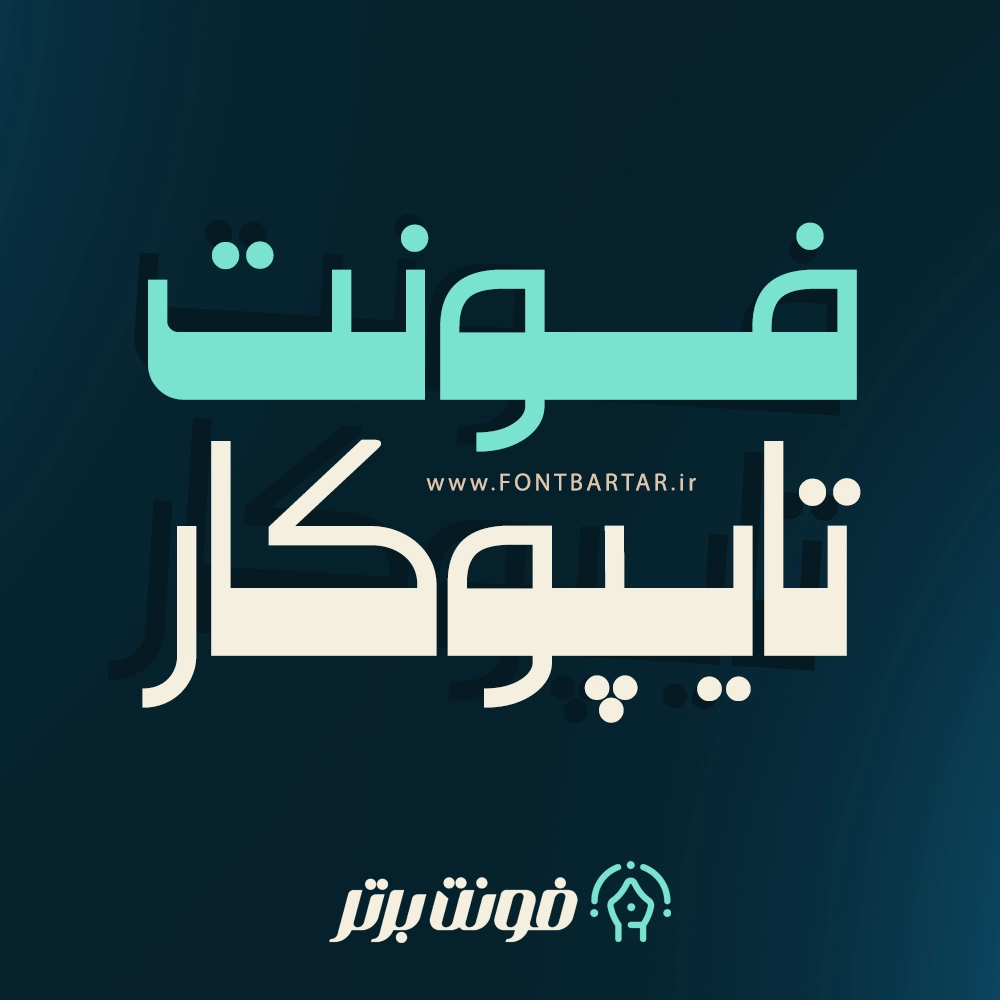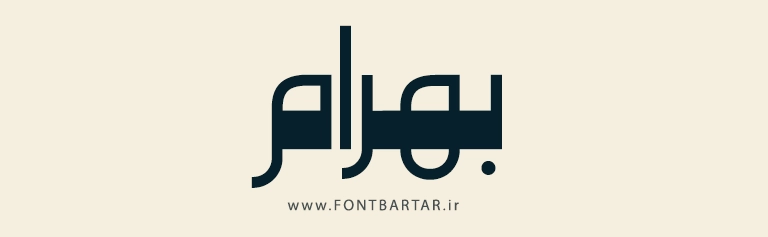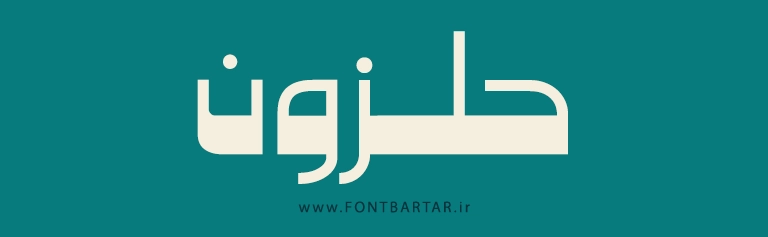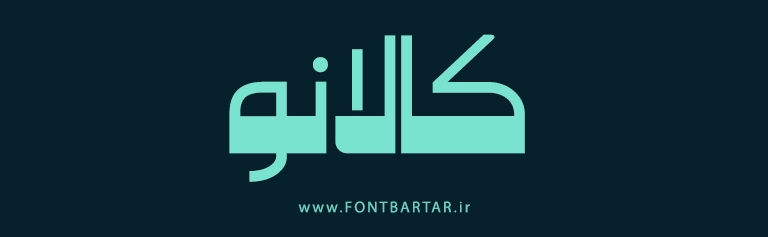
فونت زیبا و جدید تایپوکار
فونت خاص تایپوکار یک فونت منحصر به فرد و خلاقانه است که به دلیل طراحی خاص و جذاب خود، به عنوان یکی از بهترین انتخابها برای پروژههای تایپوگرافی فارسی شناخته میشود. این فونت برای طراحان گرافیک، وبسایتها و چاپگرها یک گزینه عالی محسوب میشود. در این مقاله، نحوه دانلود و استفاده از فونت خاص فارسی و کاربردهای آن را بررسی خواهیم کرد.
دانلود فونت خاص تایپوکار برای طراحی گرافیکی و تایپوگرافی فارسی
فونت تایپوکار به طور خاص برای ایجاد تایپوگرافیهای زیبا و چشمنواز طراحی شده است. این فونت ترکیبی از خطوط منحنی و زاویههای دقیق است که به متنی که در آن استفاده میشود، جذابیت و شخصیت خاصی میدهد. از این خرید فونت خاص میتوان در طراحی لوگو، بنرهای تبلیغاتی، و محتوای وبسایت استفاده کرد. طراحی آن به گونهای است که هم در اندازههای بزرگ و هم کوچک به وضوح قابل خواندن است.
مزایای طراحی با فونت خاص از فونت تایپوکار در طراحیهای گرافیکی
- ظاهر مدرن و خلاقانه: طراحی فونت تایپوکار باعث میشود تا هر پروژه طراحی، جلوهای مدرن و حرفهای داشته باشد.
- قابلیت خوانایی بالا: فونت خرید این فونت در اندازههای مختلف بسیار خوانا است.
- سازگاری با زبان فارسی: فونت تایپوکار به طور کامل از حروف فارسی پشتیبانی میکند و میتوان آن را در تمام پروژههای فارسی زبان استفاده کرد.
اگر به دنبال یک فونت خاص و زیبا برای طراحیهای گرافیکی و تایپوگرافی فارسی هستید، فونت تایپوکار یک انتخاب عالی است. با قابلیتهای متنوع و طراحی منحصر به فرد آن، این فونت میتواند پروژههای شما را به سطح بالاتری ارتقا دهد.